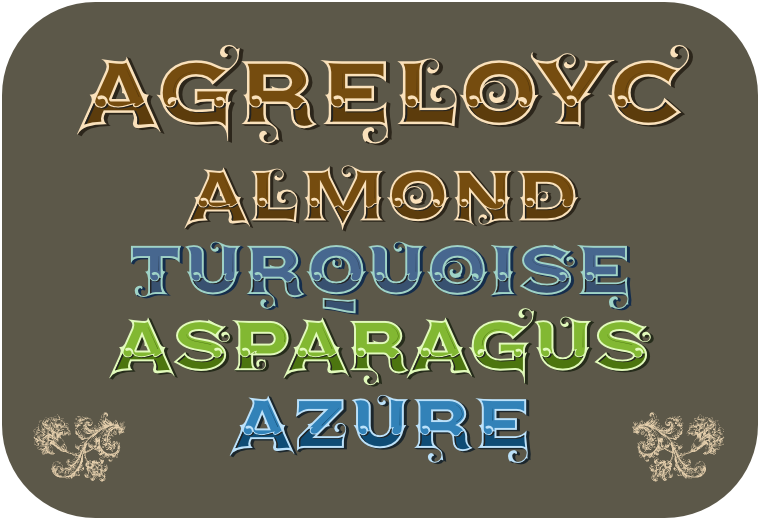
SVGinOT Agreloyc: Almond, Turquoise, Azure i Asparagus są kolorowymi fontami z wpisanymi na stałe wartościami kolorów w nowym formacie. OpenType SVG font jest propozycją wielokolorowego, wektorowego formatu fontów i został zaimplementowany w Mozilla Firefox (v. >= 26), Microsoft Edge (v. >= 38.14393), Adobe Illustrator CC 2018 i Adobe Photoshop CC 2017.